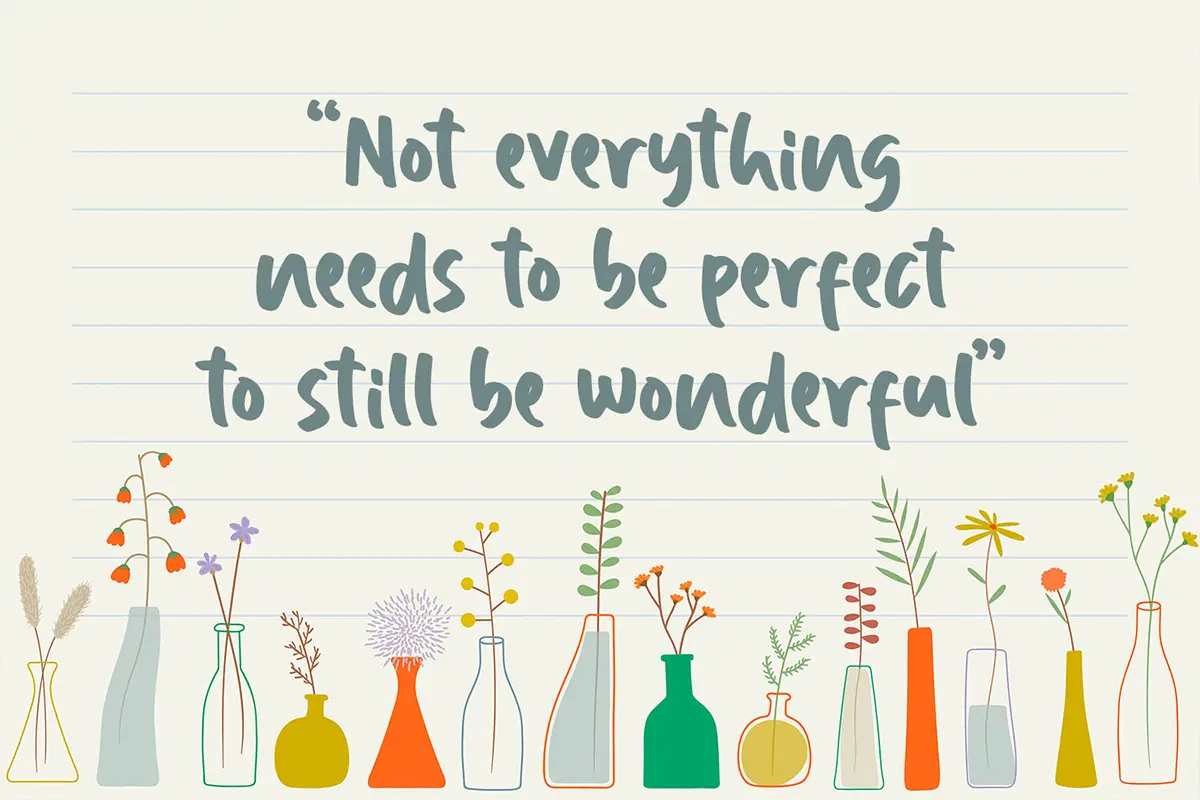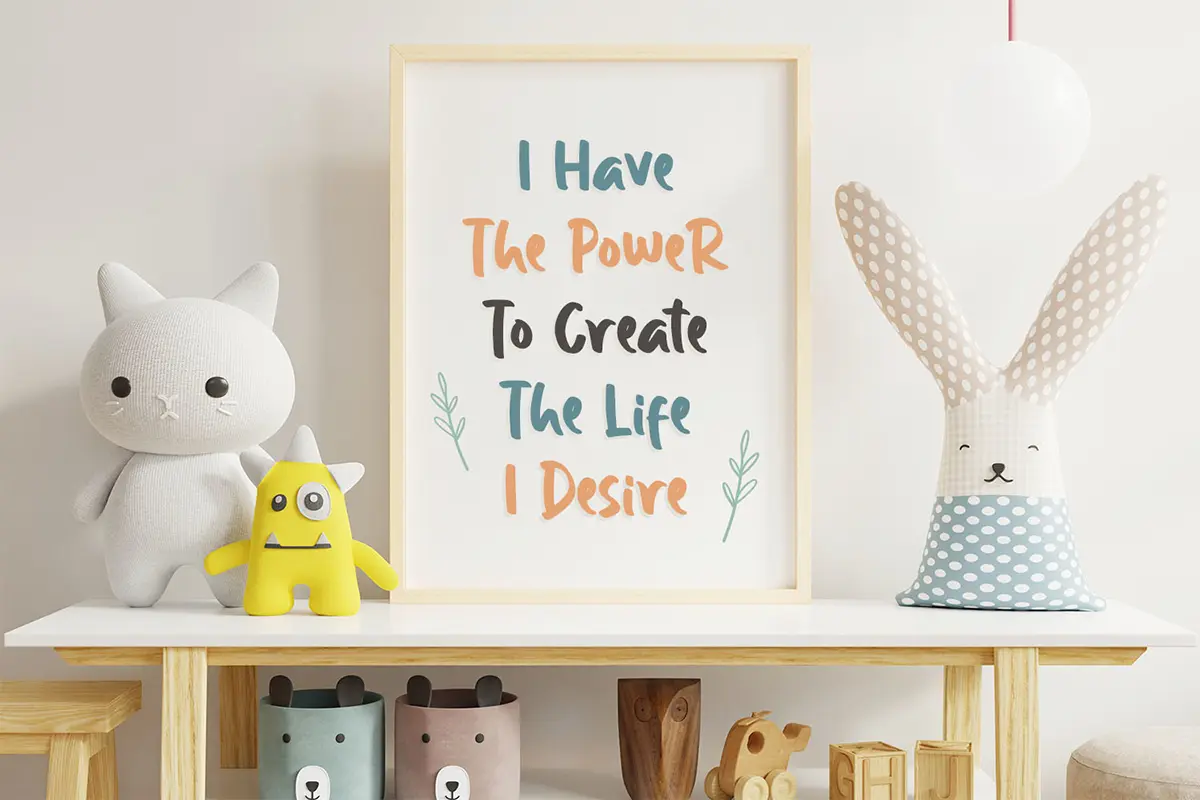
فونت بامزه و جذاب
فونت Daily Keisha یک فونت نمایشی بامزه و جذابه که با سبک فانتزی و کمی غیرمعمول خودش میتونه به طراحیهای شما حالوهوای شاد و روشن بده. این فونت برای پروژههای خلاقانه عالیه و بهراحتی میتونی اون رو به طرحهات اضافه کنی و از نتیجه لذت ببری.
⭐ ویژگیهای محصول
- فونت نمایشی با سبک فانتزی و شاد
- مناسب برای پروژههای خلاقانه و کودکانه
- اضافه کردن حس سرزندگی و جذابیت به طراحیها
🎯 موارد استفاده
- طراحی پوسترها و فلایرهای سرگرمکننده
- ساخت کارتهای تبریک و دعوتنامهها
- استفاده در محصولات چاپی مثل تیشرت، کیف و لیبل
- تزئین محتوای دیجیتال و شبکههای اجتماعی